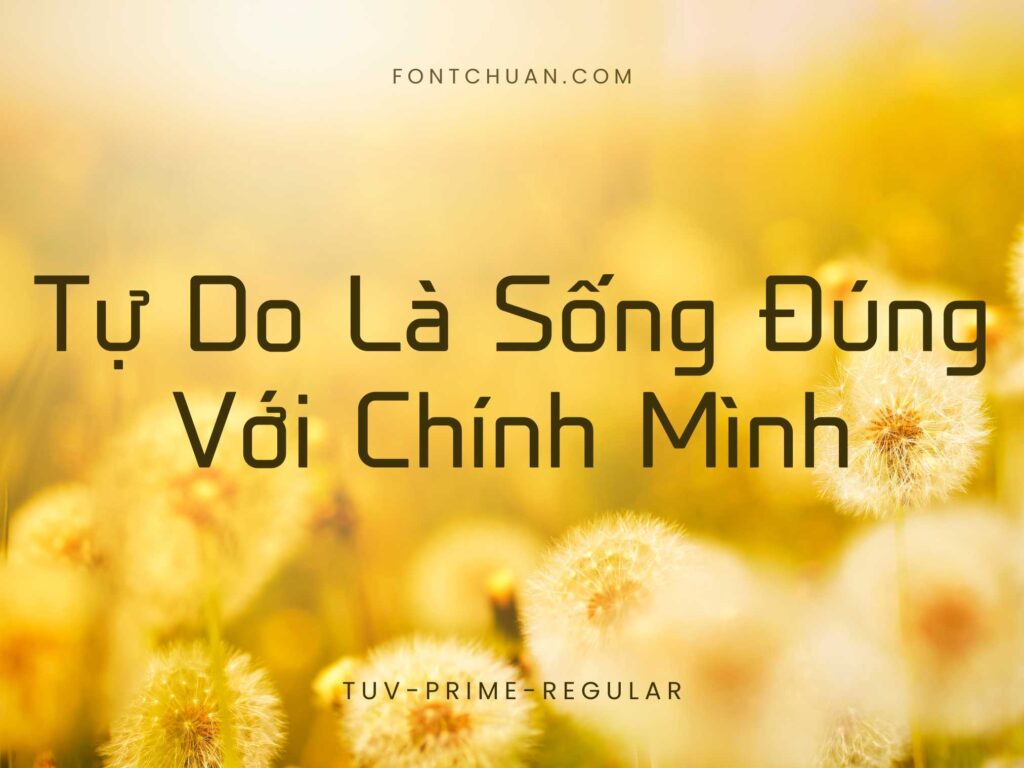
Font TUV Prime Regular Việt Hóa
Prime là một font chữ sans-serif hiện đại, được thiết kế bởi Max Pirsky. Font này có thiết kế hình học sạch sẽ với thẩm mỹ hiện đại. Các ký tự được cấu trúc đồng đều, mang lại cảm giác cân bằng và chính xác. Chữ hoa và chữ thường duy trì chiều cao nhất quán, góp phần tạo nên vẻ ngoài gọn gàng. Các chữ số rõ ràng và dễ đọc, phù hợp cho nhiều ứng dụng khác nhau. Các ký tự đặc biệt được xác định rõ, tăng cường tính linh hoạt của font. Thiết kế tổng thể tối giản, tập trung vào sự rõ ràng và chức năng, làm cho nó lý tưởng cho các dự án đương đại. Font đã được Việt hóa để hỗ trợ tiếng Việt bởi Thùy Uyên, giúp người dùng Việt Nam dễ dàng áp dụng trong các dự án thiết kế. Font này được sưu tầm và chia sẻ bởi thành viên của Font Chuẩn, đáp ứng nhu cầu sử dụng đa dạng trong cộng đồng thiết kế.
Đặc điểm thiết kế của Prime bao gồm các hình dạng hình học sạch sẽ và chính xác, tạo cảm giác hiện đại và tinh tế. Font này phù hợp cho các ứng dụng như thiết kế logo, tiêu đề, giao diện người dùng và các dự án sáng tạo khác. Các ngành nghề phù hợp bao gồm công nghệ, quảng cáo và giáo dục.